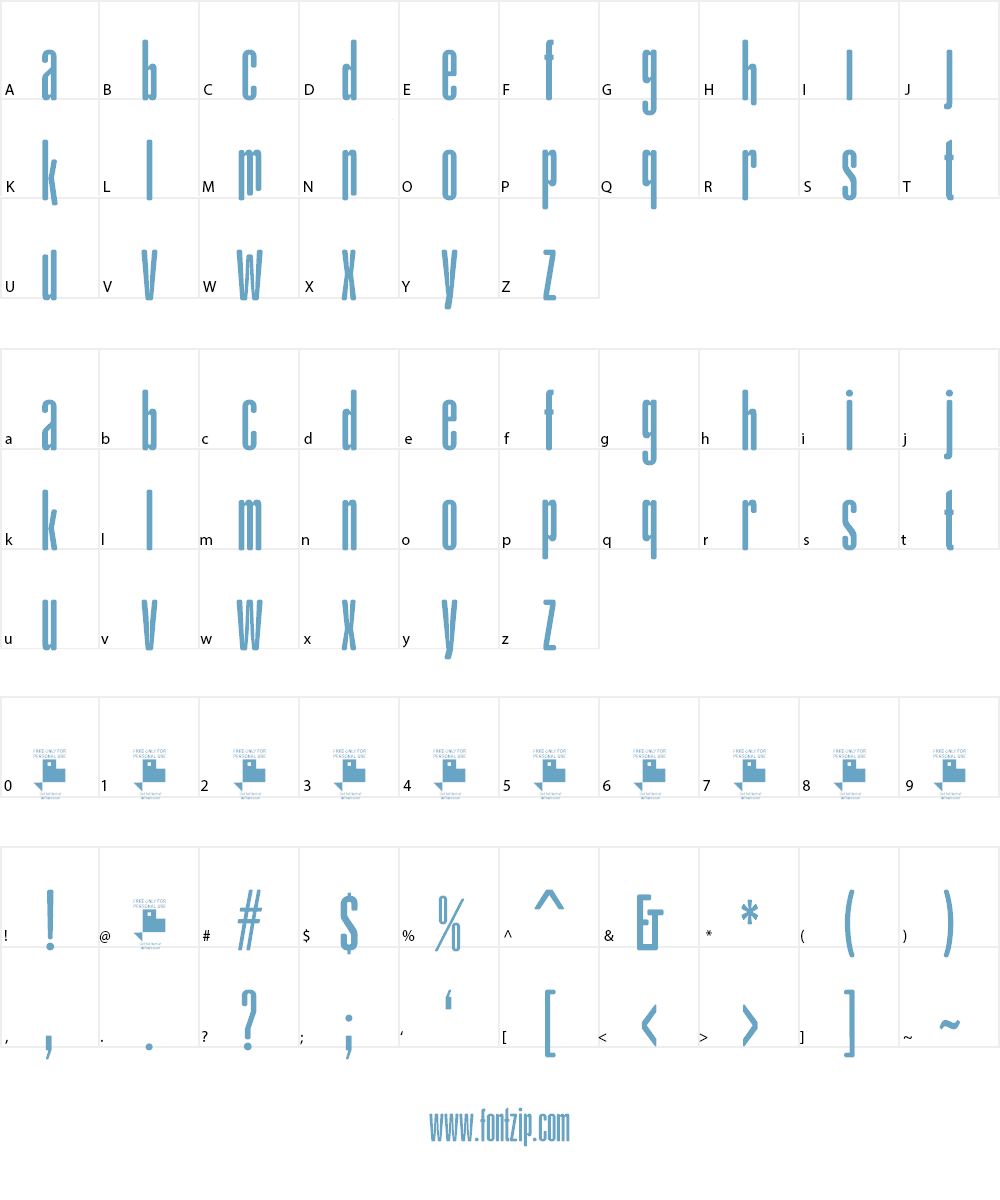
Nueva tipografía sans hiper comprimida en minúsculas, con funciones OTF para diseño gráfico.
New sans and hyper compressed lowercase typography, with OTF functions for graphic design.